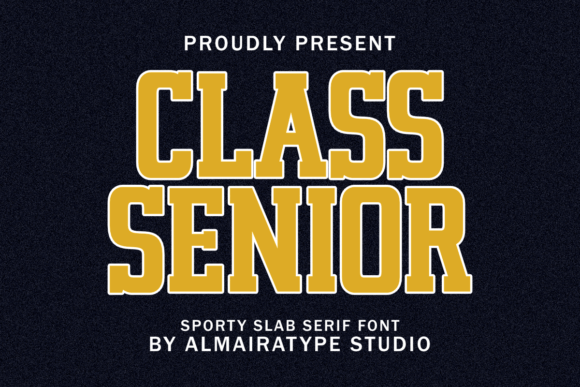
Class Senior
Trouver les bons éléments de conception peut être un défi, mais Class Senior propose une collection exceptionnelle qui rehausse instantanément votre travail.
Conçu avec précision, Class Senior offre des vecteurs nets, une typographie fluide et une licence commerciale pour une tranquillité d'esprit.
Que vous créiez des produits POD (impression à la demande), des invitations de mariage ou des visuels pour les réseaux sociaux, Class Senior est un choix idéal.